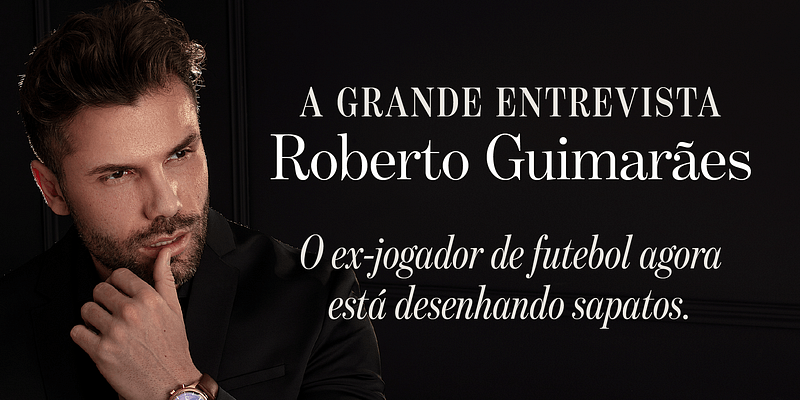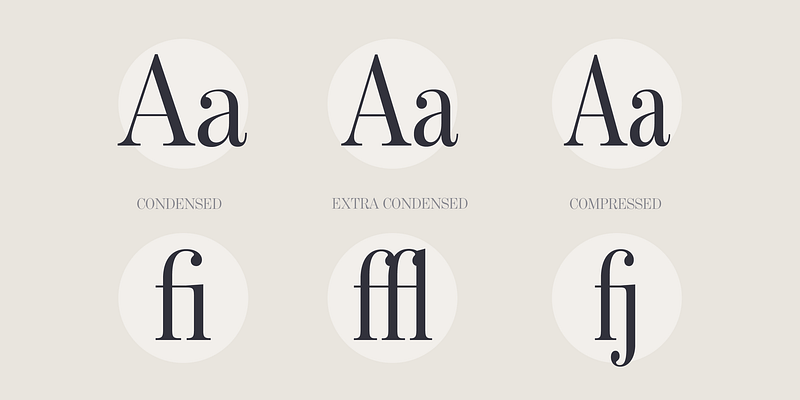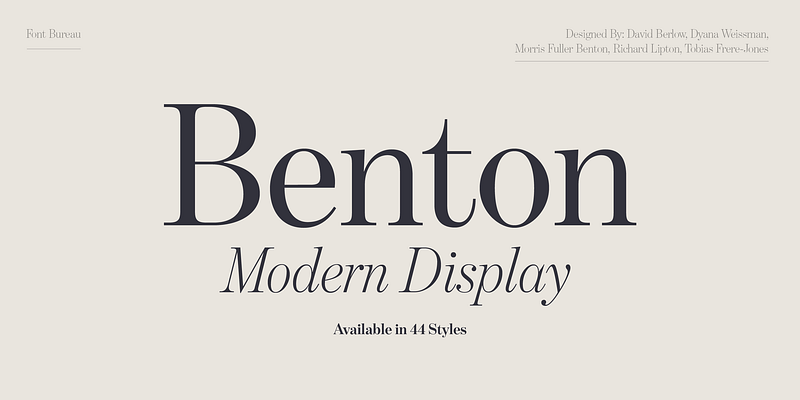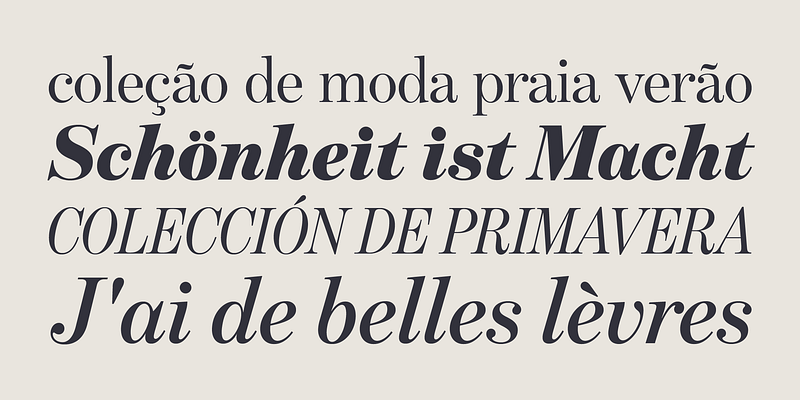
Benton Modern은 처음에 Font Bureau에서 Boston Globe와 Detroit Free Press를 위한 텍스트 서체로 제작되었습니다. 디자인과 비율은 ATF를 위해 제작된 Morris Fuller Benton의 세기말 Century Expanded에서 따왔으며, 획기적인 잡지와 뉴스 텍스트 로마체를 충실히 복원했습니다. 이탤릭체는 Century Schoolbook을 기반으로 했습니다. 이 디스플레이용 커팅은 Dyana Weissman과 Richard Lipton이 작업했습니다. FB 2008